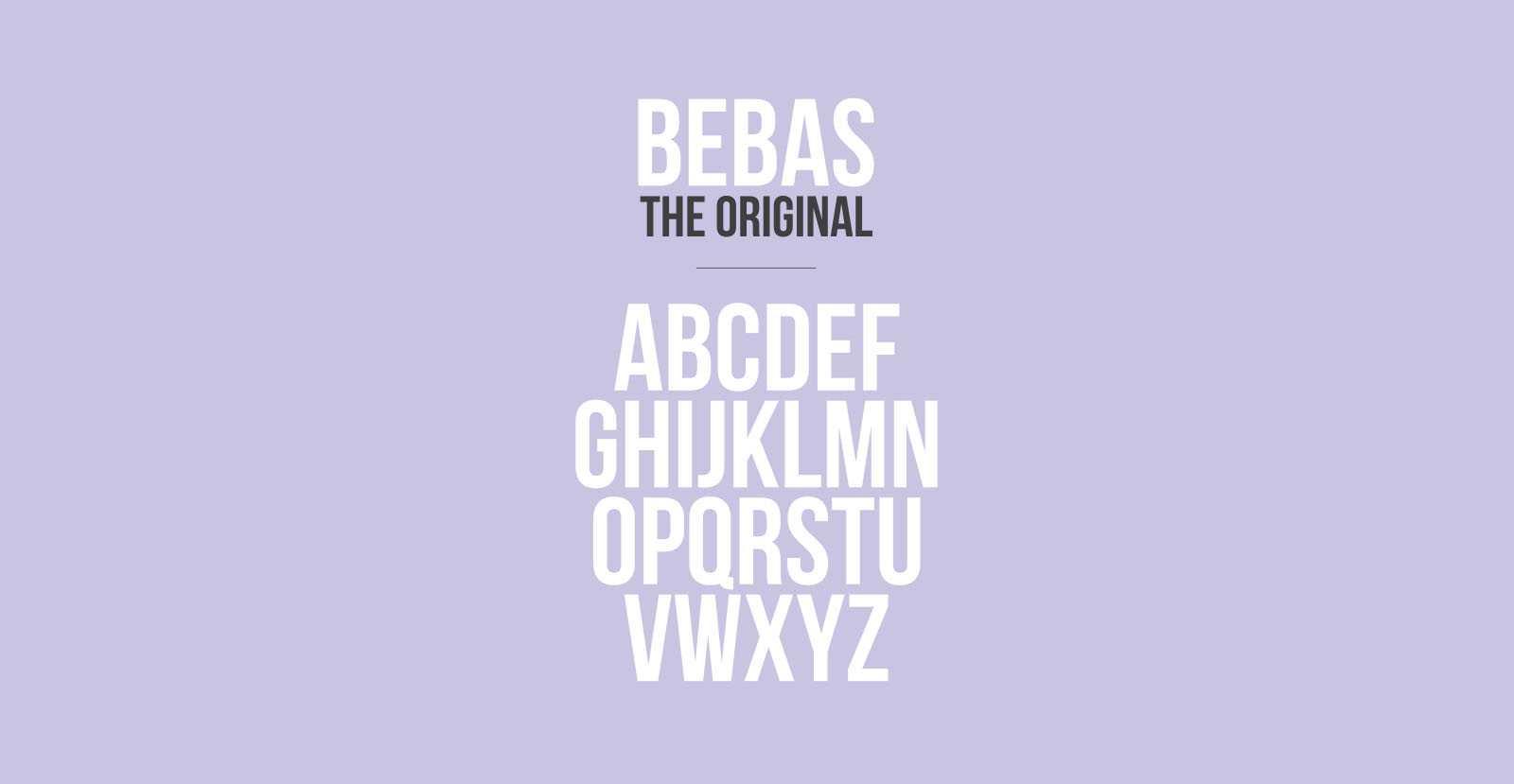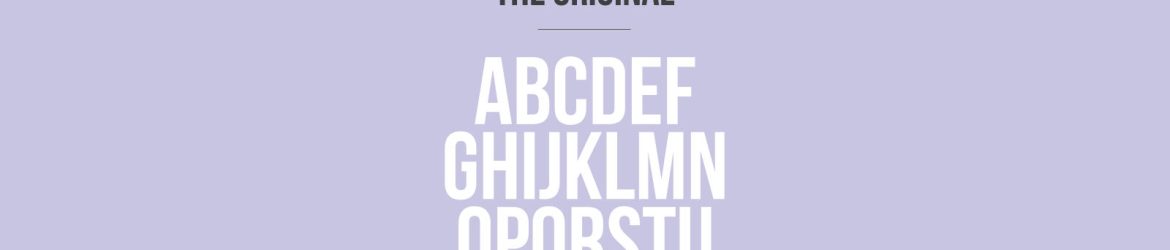
A família de fontes Bebas Condensed Uppercase é uma evolução da famosa Bebas Neue, um tipo sans serif gratuito. Conhecida por seu famoso design limpo e elegante, a Bebas Condensed Uppercase se destacou entre as fontes gratuitas. Com quatro novos pesos sub-familiares – Thin, Light, Book e Regular –, esta família de fontes agora oferece uma ampliação que atende a diferentes necessidades de design. A Bebas Condensed Uppercase se tornou tão popular que pode ser considerada o “Helvetica dos tipos gratuitos”. Suas linhas simples e formas elegantes, que incorporam uma leveza e um toque de familiaridade, tornam a Bebas Condensed Uppercase adequada para uso em web, impressão, comércio e arte. Com sua simplicidade, elegância e facilidade de uso, ela é uma excelente adição à sua biblioteca de recursos gráficos.